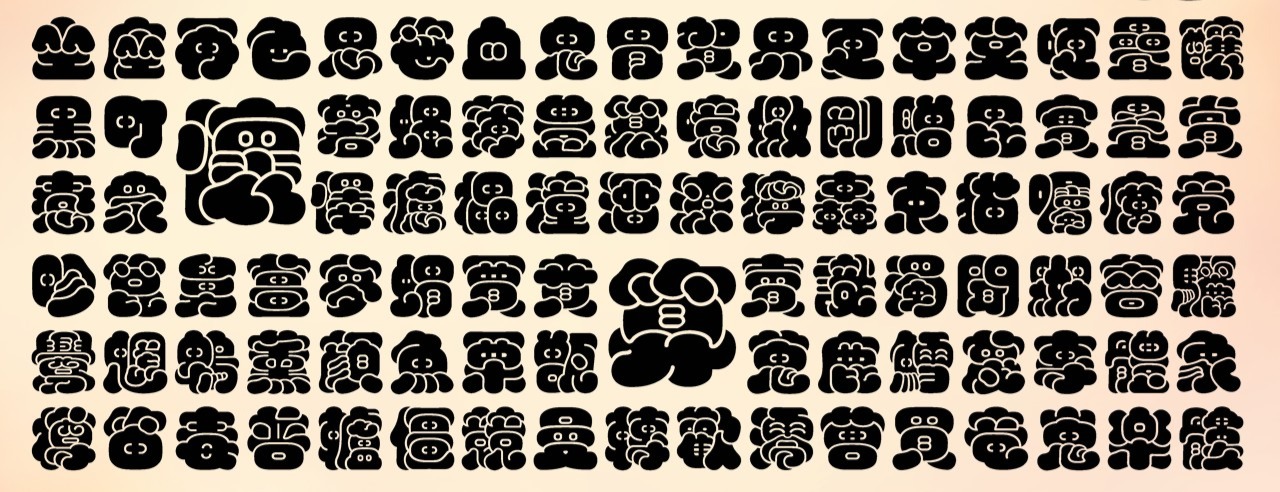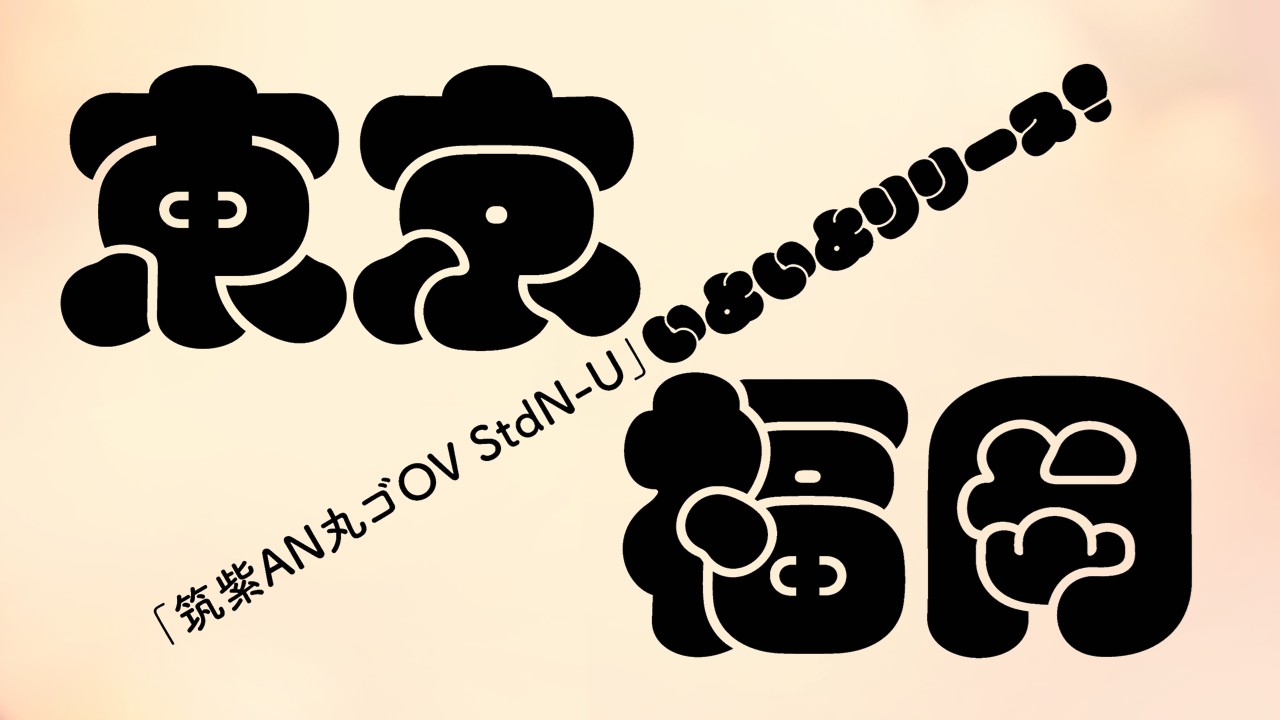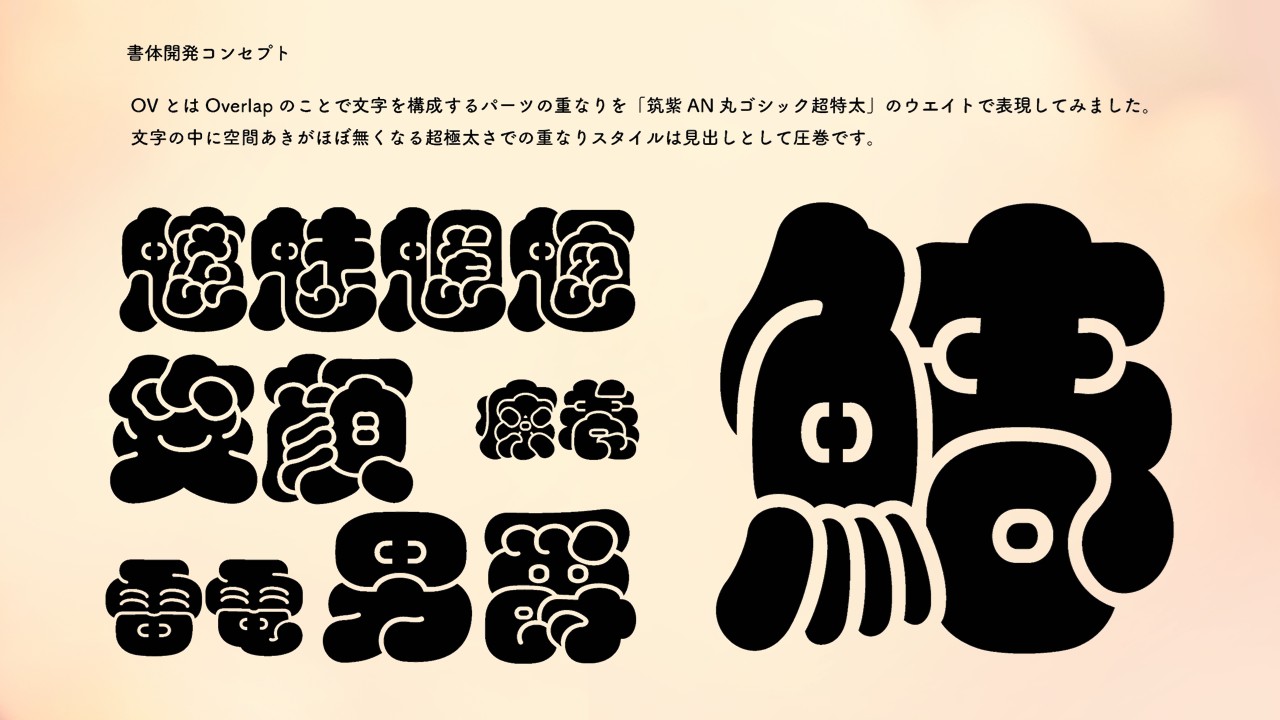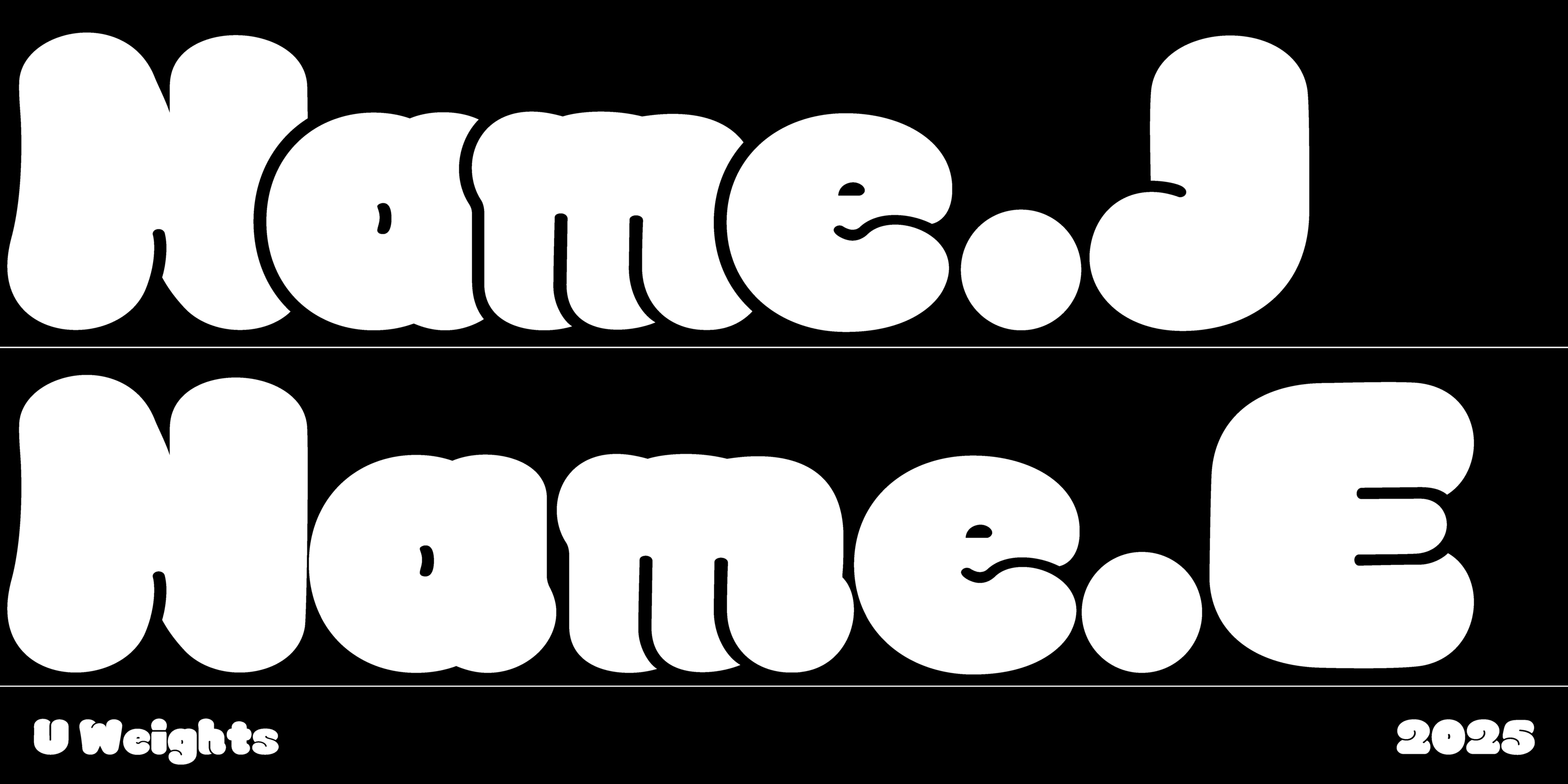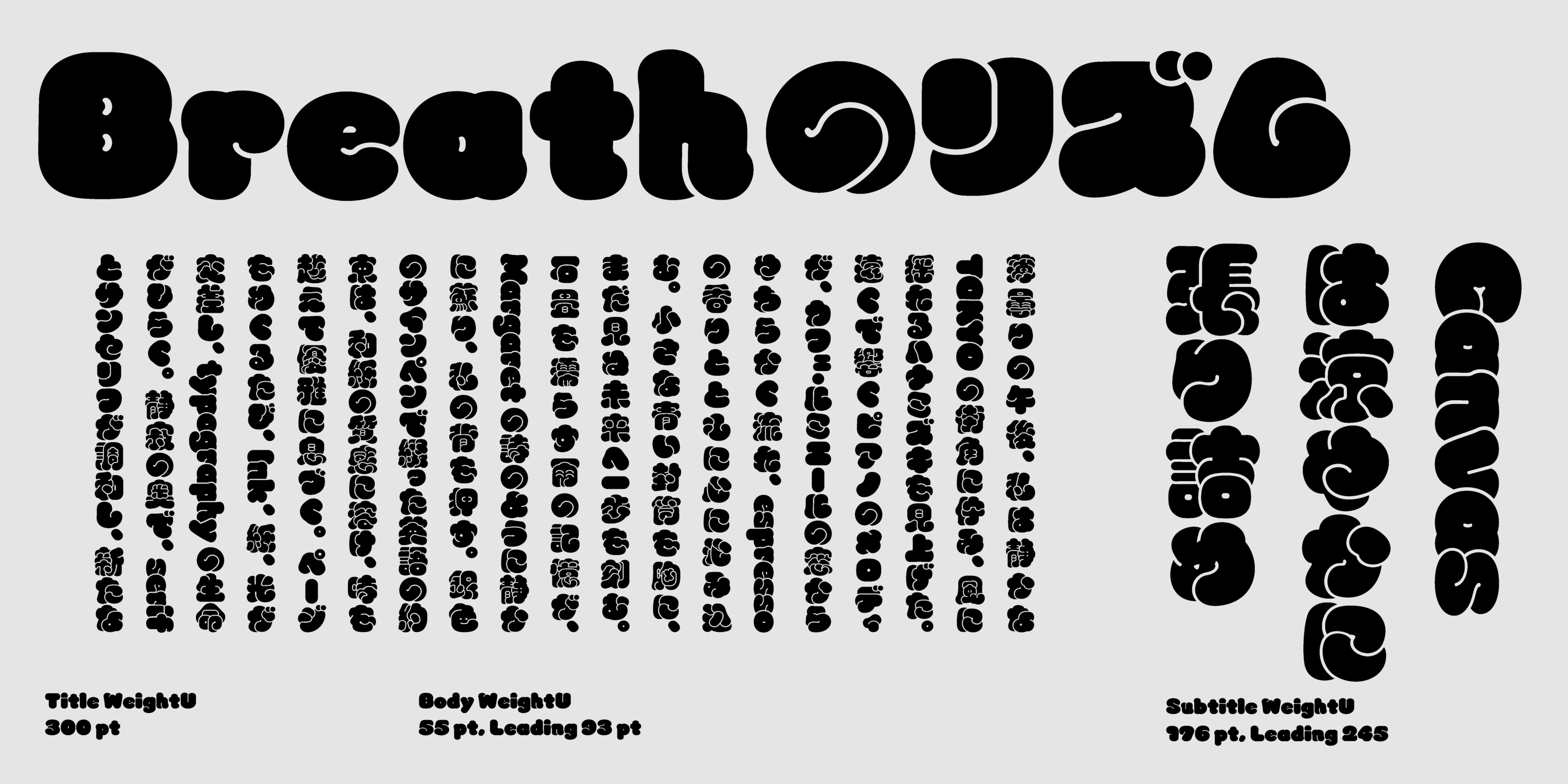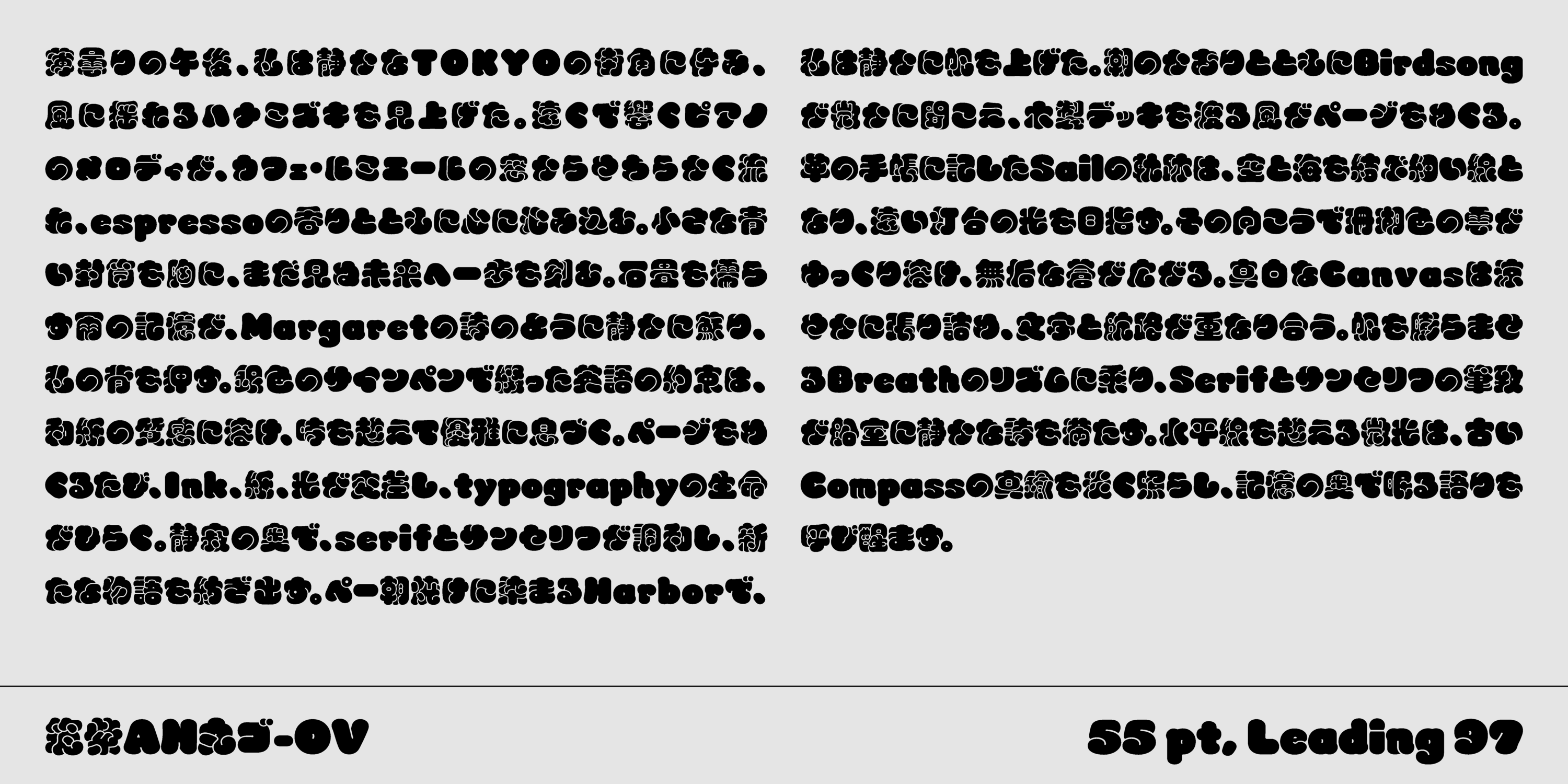
Monotype、強烈な個性と遊び心を兼ね備えたレトロモダン書体「筑紫AN丸ゴOV-U」を、フォントサービス「Monotype Fonts」に追加
筑紫AN丸ゴOV 書体開発コンセプト
筑紫書体シリーズの最新作・筑紫AN丸ゴOVは、従来の筑紫書体のイメージを覆す、新たなコンセプトで制作された書体です。 本書体は、「既存の重なりや食い込みのある書体からの脱却」をテーマに開発されました。 「OV」は「Overlap」の略で、文字を構成するパーツの重なりを筑紫AN丸ゴシックの超特太(Ultra)ウェイトで力強く表現。 筑紫AN丸ゴの「AN」は「アンティーク」を意味します。
筑紫AN丸ゴOV-U 特徴
1.強烈なインパクト
太く詰まったシルエットで、視線を一瞬で引きつけます。ロゴやタイトル、見出しなど「目立たせたい文字」に最適です。強烈なインパクトを与える事ができます。
2.柔らかさと遊び心
丸みを帯びた曲線と、内側のうねるような模様が、柔らかくポップな印象を与えます。親しみや楽しさを表現したいときに効果的です。
3.和風・レトロ感
漢字をデフォルメした独特な形が、どこか昭和レトロや日本的デザインの雰囲気を醸し出します。和風デザインやノスタルジックな演出にも向いています。
超極太のウェイトによって、文字内部の空間がほとんど消えるほどの重なりスタイルは、見出しとして圧倒的な存在感と強いインパクトを放ちます。 さらに、動物のようにも見えるユニークな文字フォルムは、文字組の世界に新たな表情と豊かさをもたらします。
2つの顔を持つ従属欧文
欧文は単語内で自然に重なるように設計されています。文章にしたときもみっちり詰まった印象を残しつつ読みさすさを実現しています。英数字の並びが2種類(ノーマル・食い込み)あり、用途に応じての使い分けが可能です。